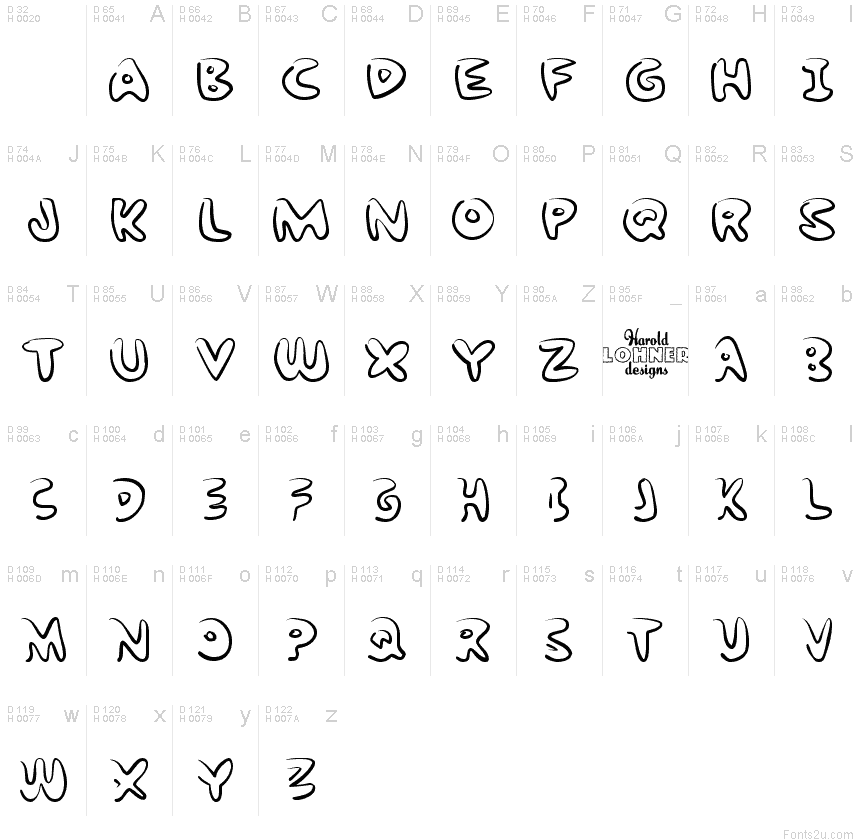
Bubble Gum Rock A di Harold Lohner è un font decorativo cartoon gratuito che sembra disegnato con un pennarello spesso e ricco d'inchiostro. Le lettere, traballanti e gonfie, con i loro contorni morbidi e arrotondati e i divertenti puntini interni, donano a ogni parola un'energia vivace e fatta a mano. Ha un carattere amichevole e informale che salta subito all'occhio senza risultare disordinato, specialmente se utilizzato in grande e in grassetto, abbinato a un font sans serif pulito per il testo di supporto.
Con Bubble Gum Rock A, trasforma all'istante titoli semplici in dichiarazioni vivaci e colorate. Il suo ritmo disinvolto e le curve accentuate sono perfetti per copertine di libri per bambini, inviti a feste, packaging creativo, poster, adesivi e grafiche divertenti per i social. Mantieni le righe brevi e dai alle lettere il giusto spazio, così le forme frizzanti rimarranno leggibili pur conservando il loro spirito gioioso e divertente.